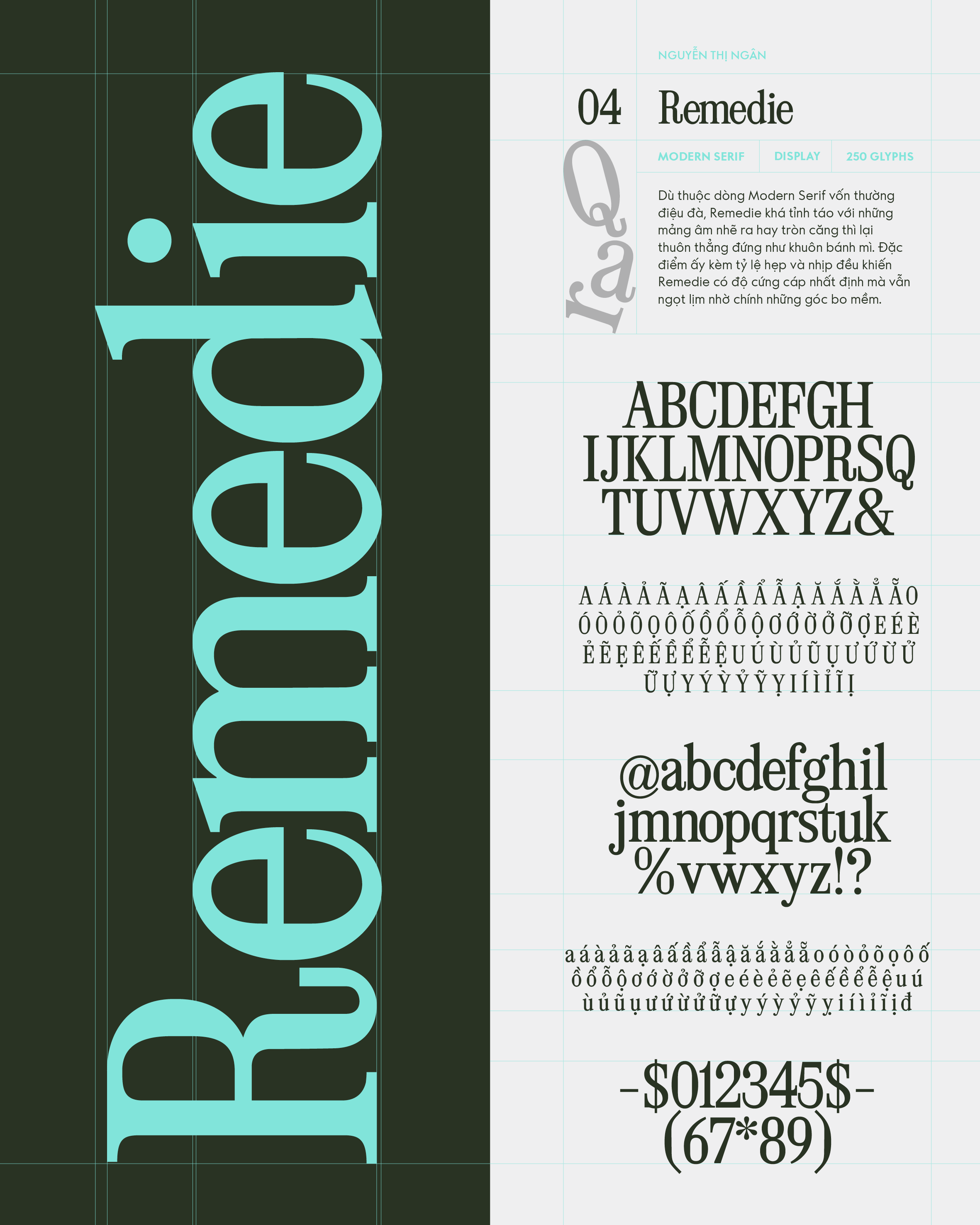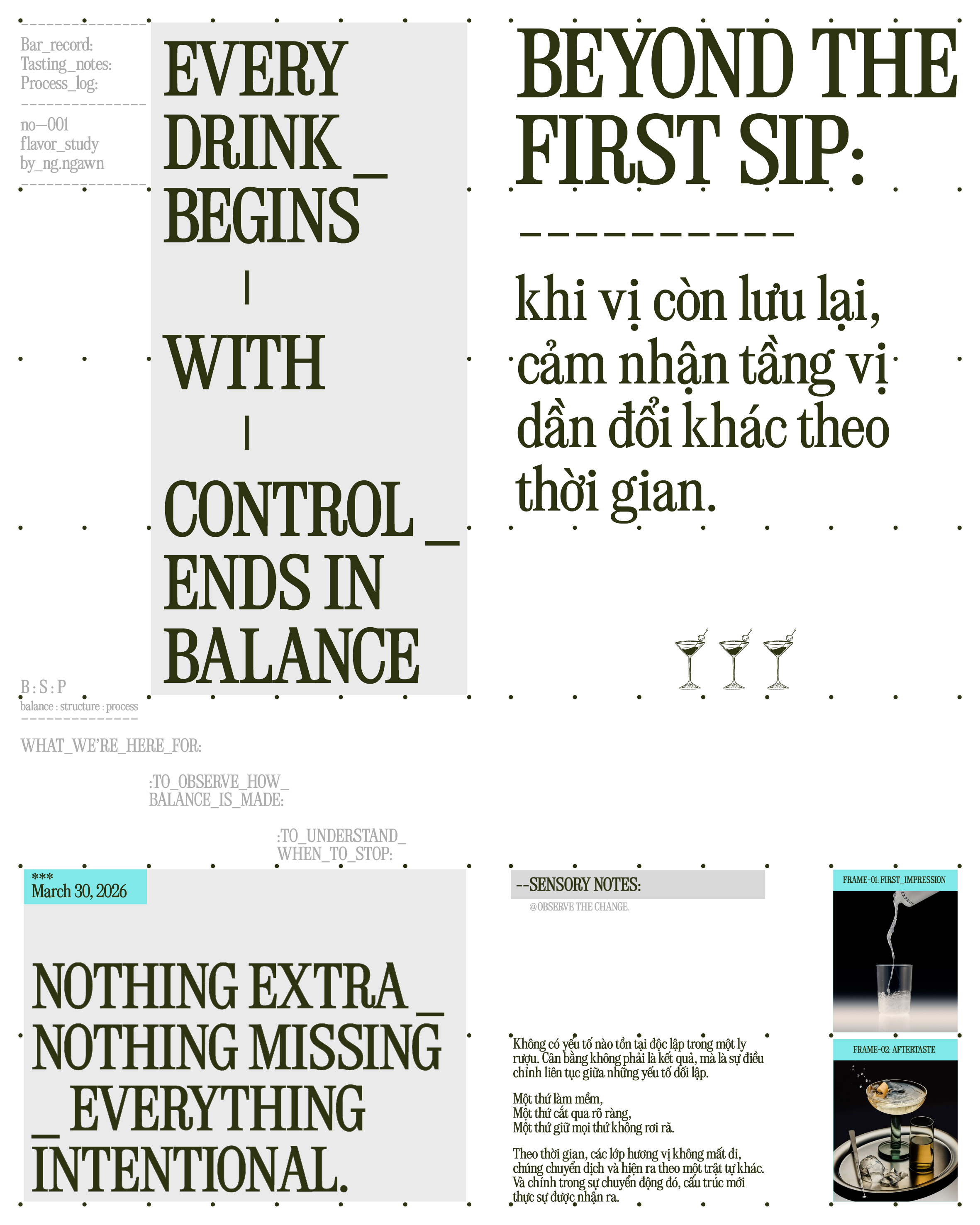
Remedie
Về Remedie: Dù thuộc dòng Modern Serif vốn thường điệu đà, Remedie khá tỉnh táo với những mảng âm nhẽ ra hay tròn căng thì lại thuôn thẳng đứng như khuôn bánh mì. Đặc điểm ấy kèm tỷ lệ hẹp và nhịp đều khiến Remedie có độ cứng cáp nhất định mà vẫn ngọt lịm nhờ chính những góc bo mềm.
Modern Serif
Display
Nguyễn Thị Ngân